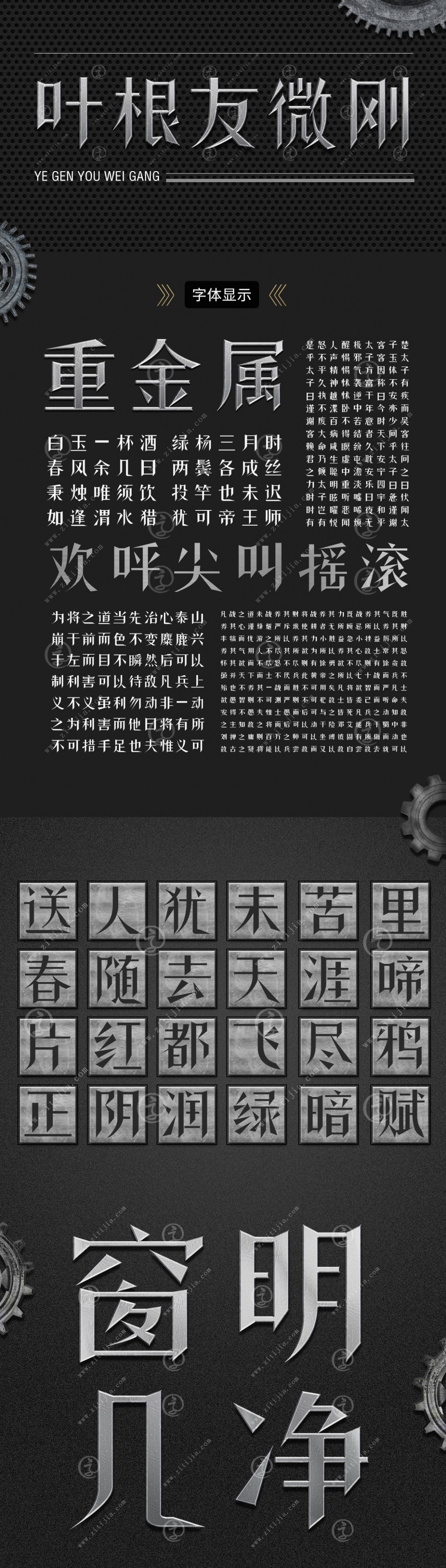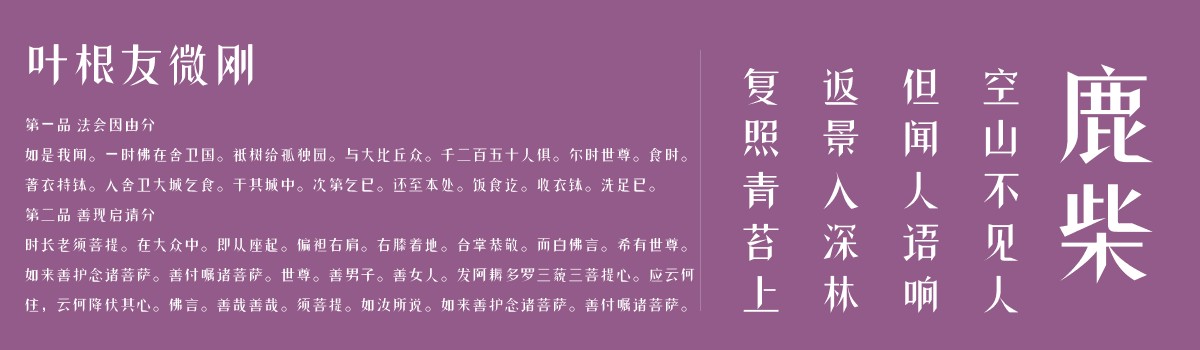
叶根友微刚
字体作者:叶根友
创作年代:2015年
2014年6月,该字体的初步设计理念画出
2014年8月,开始设计中文字形,三个月做了450个汉字
2014年12月,1200个汉字制作完毕
2015年3月,1800个汉字制作完毕
2015年8月,6763个汉字制作完毕
2015年10,最后微调
2015年12月,测试,并修正了部分字的笔画和修改了赱之底的字形
2016年2月,正式发布